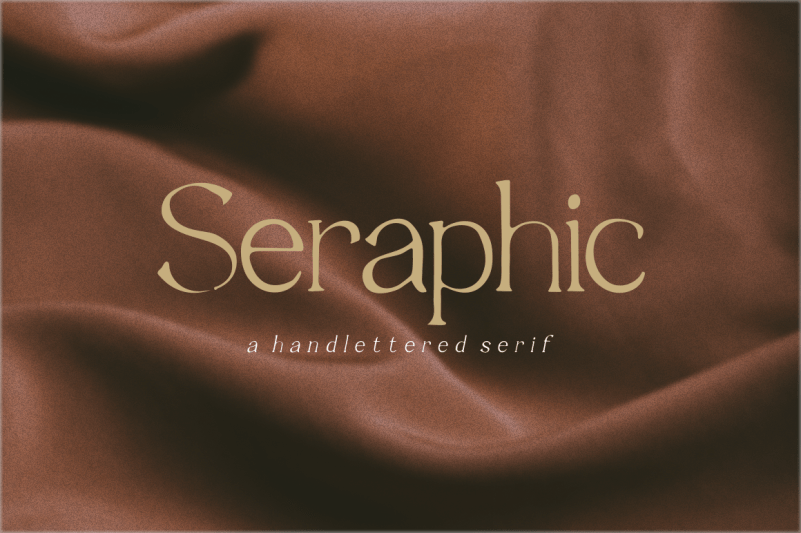
Introduzimos a Seraphic Serif Font, uma elegante fonte serif escrita à mão com um toque romântico. Ela carrega um encanto místico e delicado que pode adicionar um toque de romance aos seus projetos. Suave e linda, a Seraphic Serif é perfeita para qualquer aplicação onde você deseja transmitir uma mensagem suavemente respeitosa e romântica. Seja para criar cartas personalizadas ou até mesmo para adicionar um toque delicado em designs de moda e decoração, esta fonte será certamente sua escolha perfeita.